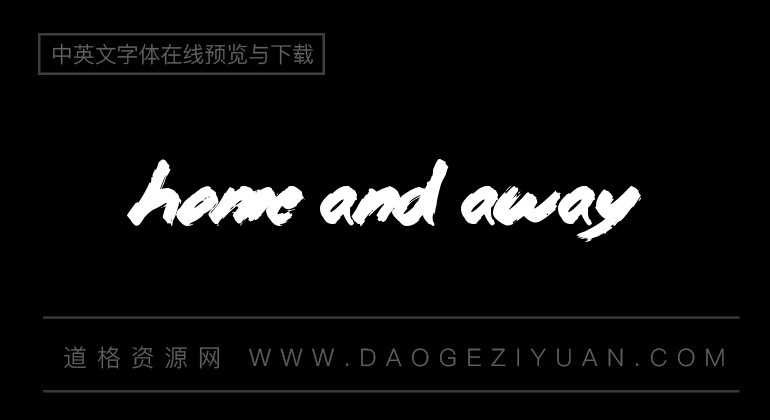
Home and Away 是一种基于手写字体的装饰性字体。它的设计灵感来源于手写字体,字母和数字的形状都像是用钢笔或毛笔书写而成的。Home and Away 字体的特点是字母和数字的线条曲折,笔画粗细不一,让字体看起来非常自然而有机。 这个字体适用于很多不同类型的设计,比如海报、宣传册、标志、卡片等等。由于它是一种装饰性字体,所以在设计中需要注意使用的场景和目的,不宜过度使用,以免影响阅读和传达信息的效果。 总的来说,Home and Away 字体是一种非常有特色的装饰性字体,可以为设计增添一些自然和手工的感觉。内容介绍
Home and Away是一款非常不错的手写艺术字体,具有很好的视觉感,适合于文化类的宣传设计、商业类品牌的广告和产品包装设计以及个性化文字排版等较多场景。